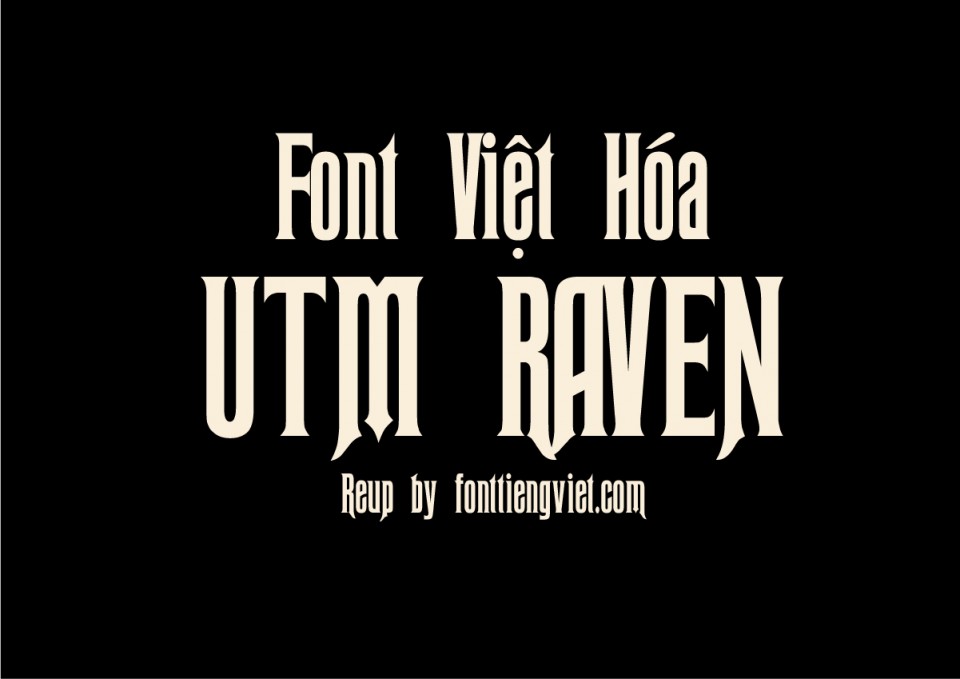
Font việt hóa UTM Raven
Tải Font việt hóa UTM Raven – Phông chữ phong cách cổ điển ấn tượng
Giới thiệu về bộ Font việt hóa UTM Raven chuyên nghiệp
Trong cộng đồng thiết kế đồ họa tại Việt Nam, Font việt hóa UTM Raven luôn là cái tên được săn đón nhờ vẻ ngoài mạnh mẽ và cá tính. Đây là một định dạng phông chữ thuộc bộ UTM nổi tiếng, giúp người dùng dễ dàng thể hiện các ý tưởng sáng tạo trên nhiều nền tảng khác nhau. Khi sử dụng Font Miễn Phí để trang trí, bạn sẽ thấy Raven mang đậm hơi hướng cổ điển nhưng không kém phần hiện đại. Việc lựa chọn đúng font chữ không chỉ giúp văn bản rõ ràng mà còn tạo nên dấu ấn riêng biệt cho mọi ấn phẩm truyền thông của bạn.
Những ưu điểm nổi bật của Font việt hóa UTM Raven
Thiết kế độc đáo và tính ứng dụng cao
Font việt hóa UTM Raven sở hữu các đường nét dứt khoát, mô phỏng phong cách chữ viết tay bằng bút lông hoặc thư pháp phương Tây. Điều này khiến font chữ cực kỳ phù hợp cho việc thiết kế bìa sách, tiêu đề báo chí hoặc các loại poster sự kiện trường học. Nhờ quá trình việt hóa chỉn chu, các ký tự có dấu trong tiếng Việt được hiển thị mượt mà, không xảy ra lỗi nhảy font khó chịu. Điều này giúp học sinh và giáo viên dễ dàng tạo ra những bài thuyết trình sinh động và chuyên nghiệp hơn.
Phù hợp cho nhiều mục đích đồ họa
Dù bạn đang thực hiện một dự án thiết kế logo hay làm thiệp mời, Raven luôn đáp ứng tốt khả năng hiển thị. Độ tương phản giữa các nét thanh và nét đậm giúp tổng thể văn bản trở nên hài hòa, lôi cuốn thị giác ngay từ cái nhìn đầu tiên. Bạn có thể kết hợp nó với các màu sắc trầm để tạo vẻ hoài cổ hoặc màu tươi sáng để tăng tính năng động.
Kết luận về bộ Font việt hóa UTM Raven
Với những giá trị thẩm mỹ tuyệt vời, Font việt hóa UTM Raven chắc chắn là công cụ không thể thiếu trong bộ sưu tập của các nhà thiết kế. Việc tận dụng nguồn tài nguyên từ Font Miễn Phí, Font Việt Hóa, Font việt hóa UTM Raven sẽ giúp bạn tiết kiệm thời gian và nâng cao chất lượng sản phẩm. Hãy tải ngay để trải nghiệm sự khác biệt mà phông chữ này mang lại cho dự án của mình.